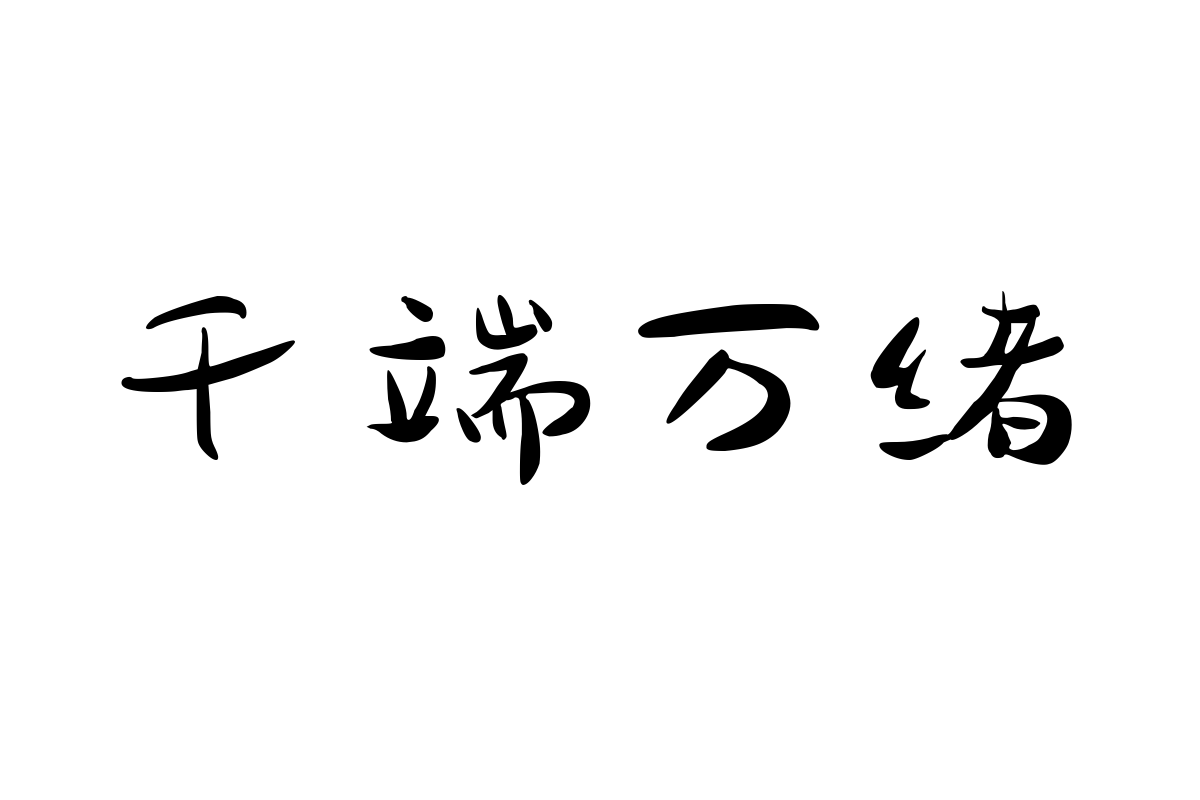
**三极夕阳漫游体是一款具有随性感和创意的字体,笔画飘逸灵动,适合用于海报标题、品牌广告等设计用途**。
三极夕阳漫游体是SJxiyangmanyou字体家族中的一个成员,该字体以其独特的字形设计和风格著称。这种字体的设计灵感来源于自然界中的夕阳景象,通过其独特的笔画和结构,给人一种轻松随性而又不失俏皮可爱的感觉。